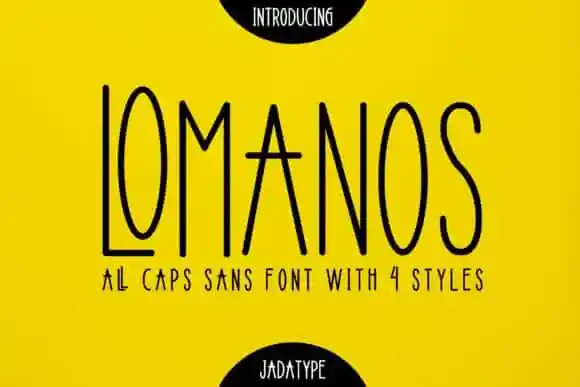
Lomanos Sans Serif Font – Download Grátis
A Lomanos Sans Serif Font é uma escolha perfeita para qualquer designer que busca um estilo moderno e elegante. Este Thin Condensed sans serif se destaca por sua simetria e facilidade de leitura, adequada para criar designs únicos e chamativos em todas as suas criações. Combinado com sua fina tipografia, a Lomanos Sans Serif é uma ótima escolha para criar o formato perfeito das suas designações nupculares, agendas de casamento ou sites, oferecendo um look delicado e feminino que se destaca entre os demais. Sua flexibilidade permite incorporá-la em diversos ambientes gráficos sem sacrificar a qualidade do seu trabalho. Esta fonte é uma verdadeira obra-prima para quem procura um estilo sofisticado e inovador, oferecendo liberdade criativa para expressar suas ideias de maneiras únicas e modernas.